2015 타이포그래픽스 : TYPOGRAPHICS 2015
지난 6월 뉴욕의 쿠퍼 유니언에서 열린 타이포그래픽 컨퍼런스는 국적과 성별 그리고 주제가 아무런 제한 없이 어울리는 생생한 현장 그 자체였다. 그동안 내가 참여했던 컨퍼런스들 가운데 진정으로 무언가를 배울 수 있었던 기회 중 하나였다.
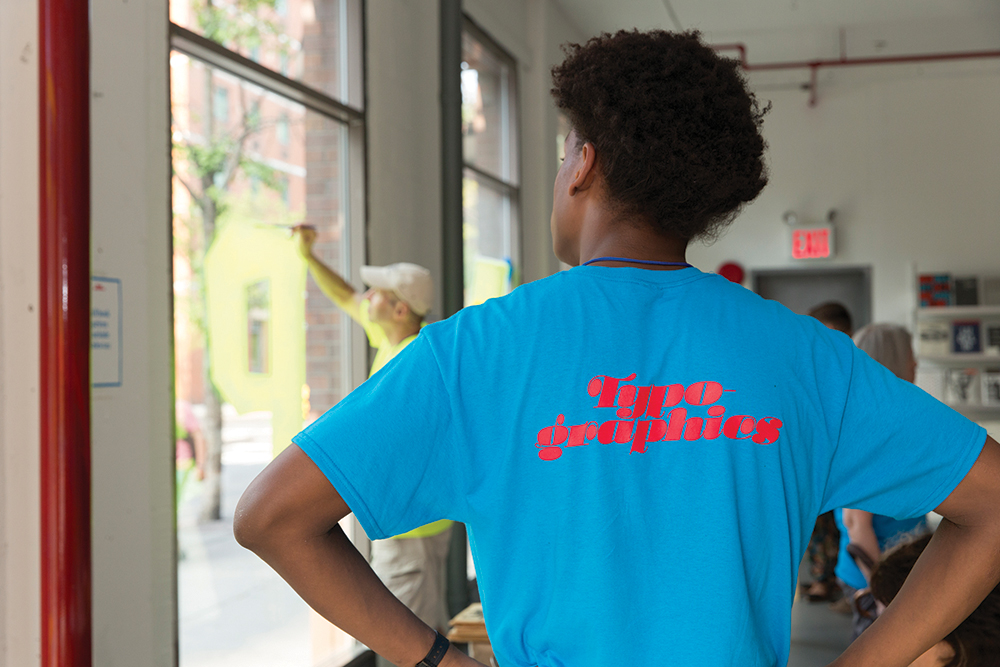
2015 타이포그래픽스
열흘 간 진행된 컨퍼런스를 통해 타입의 진화 양상에 대해 살펴보자.
지난 6월 뉴욕의 쿠퍼 유니언에서 열린 타이포그래픽 컨퍼런스는 국적과 성별 그리고 주제가 아무런 제한 없이 어울리는 생생한 현장 그 자체였다. 그동안 내가 참여했던 컨퍼런스들 가운데 진정으로 무언가를 배울 수 있었던 기회 중 하나였다. 나는 강연자로 이 행사에 참여했다.
이번 컨퍼런스에서는 강연자들 대부분이 교육적인 성격의 강연을 펼쳤다. 그들 중 몇몇은 튜토리얼이라 봐도 무방한 내용을 소개하기도 했다. 이 같은 교육적인 성격은 열흘간의 워크숍, 공연, 해커톤 대회를 거치며 점점 더 강화되어 갔다. 간판 제작 방법에서부터, 컴퓨터 과학에서 박사 학위가 중시되는 현실을 상기시키는 학사 관리 문제에 이르기까지 폭넓은 주제들이 거론됐다.
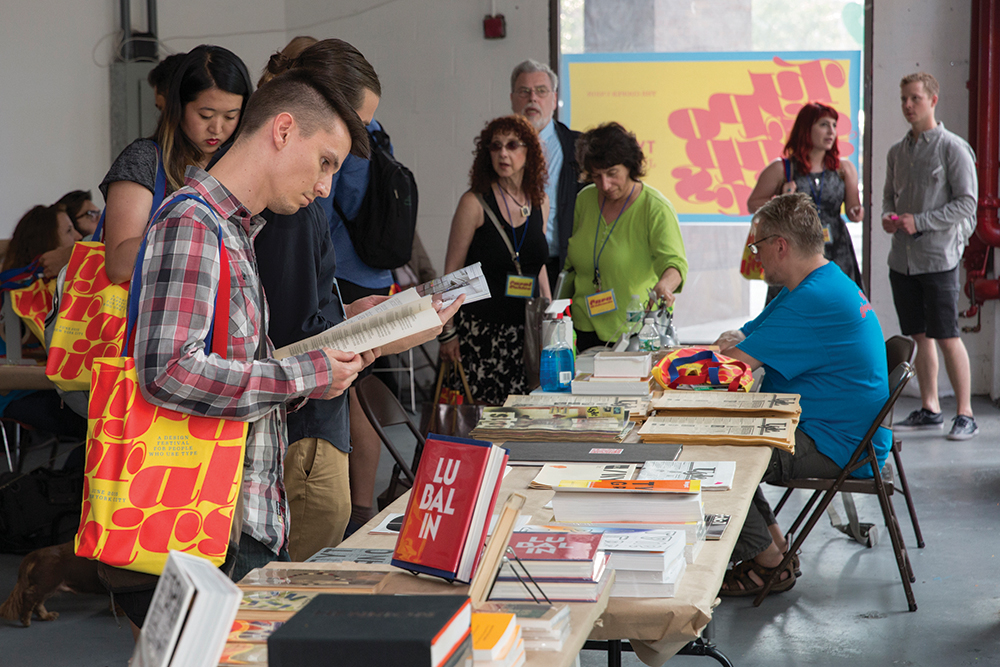
그러나 무엇보다 이번 타이포그래픽스 컨퍼런스의 가장 큰 특징은 강연자들이 타이포그래피를 언어 전반의 영역으로 광범위하게 다루었다는 점이다. 나는 특히 코드에 대한 마르코 듀고니이치(Marko Dugonjić)의 강연에 큰 감명을 받았다. 수학하고는 담을 쌓고 살아온 나로서도 처음으로 코딩을 시도해볼 수 있겠다는 마음을 들게 했다. 물론 몇 번의 시도 끝에 역시나 내 코딩 실력은 여전히 한참 멀었다는 결론이 나기는 했지만 말이다.
지금과 같은 반응형의 시대에서 타이포그래피라는 주제는 컨퍼런스의 단골 테마일 수밖에 없다. 타입 디자이너를 위한 정밀한 디지털 툴을 만드는 프로그래머로 자신을 소개한 에릭 판블록클랜드(Erik van Blokland)는 멋진 강연을 통해 오늘날 타이포그래피가 멀티 스크린, 멀티 플랫폼의 유동적인 환경에 적응해야 한다고 강조하면서 정적인 글자형태는 더 이상 여기에 적합하지 않다고 주장했다. 그러면서 그는 매개변수에 의한 글자형태(parametric letterform)의 사례들을 공개했다. 새로운 지평이 열리는 순간이었다.
반면, 몇몇 디자이너들은 이와 대척점에 선 입장을 보여줬다. 이들은 디지털 툴의 보편화가 이루어지기 전에 이미 성공한 디자이너로 입지를 굳힌 사람들이다. ‘좋았던 지난날, 힘들었던 지난날(The Good Old Days, The Bad Old Days)’이라는 제목의 강연에서 루이스 필리(Louise Fili), 스티븐 헬러(Steven Heller), 시무어 쿼스트(Seymour Chwast) 그리고 폴라 셰어(Paula Scher)는 디지털 툴을 사용하지 않았던 시절의 작업들이 주었던 재미와 혼돈을 추억하게 만들었다. 특히 스티븐 헬러는 줄자를 이용한 작업 사례를 보여줬고, 자신이 만든 1960년대 스타일의 디자인 작품들을 공개했다. 1960년대는 1/4인치 블랙 규칙이 지배하던 시절이었는데 사실 어찌 보면 일반적인 소프트웨어보다 더 많은 규칙들이 존재했던 시절이었다.
아난드 나오렘(Anand Naorem)과 닐라카쉬 크쉐트리마윰(Neelakash Kshetrimayum)의 강연에선 다음과 같은 질문이 제기됐다. “인도처럼 다양한 문화와 언어가 존재하는 복합적인 성격의 국가에서 브랜딩, 디스플레이, 텍스트 등 타이포그래피적인 커뮤니케이션을 시도하려면 어떻게 해야 할까? 우리가 어떻게 라틴의 글자형태들로 무수한 인도계 말들을 표현해 낼 수 있을까?” 이들의 지적인 강연과 큰 대비를 이루는 것이 디자이너인 마테오 볼로냐(Matteo Bologna)의 해학적인 강연이었다. 타입을 도외시하는 디자이너를 등장시켜 웃음을 유발하는 내용이었는데 물론 이 디자이너는 가상의 인물이었다.
내가 이번 타이포그래픽스 컨퍼런스에서 느낀 한 가지 불만이라면 기업 쪽 강연자들이 자기 기업의 관점에서 타입의 세계를 바라본다는 점이었다. 이는 아마도 기업에 대한 나의 반감 때문이기도 하겠지만, 내 귀에는 그들의 강연 내용이 다소 편협하고 건방지게 들렸던 것이 사실이다. 어쩌면 그들도 독립적으로 활동하는 디자이너들을 이상하게 바라봤을지도 모르겠다. 그러나 나로서는 기업 디자이너들이 기업의 영역에서 좀 더 벗어나야 한다는 생각을 멈추기가 어렵다.